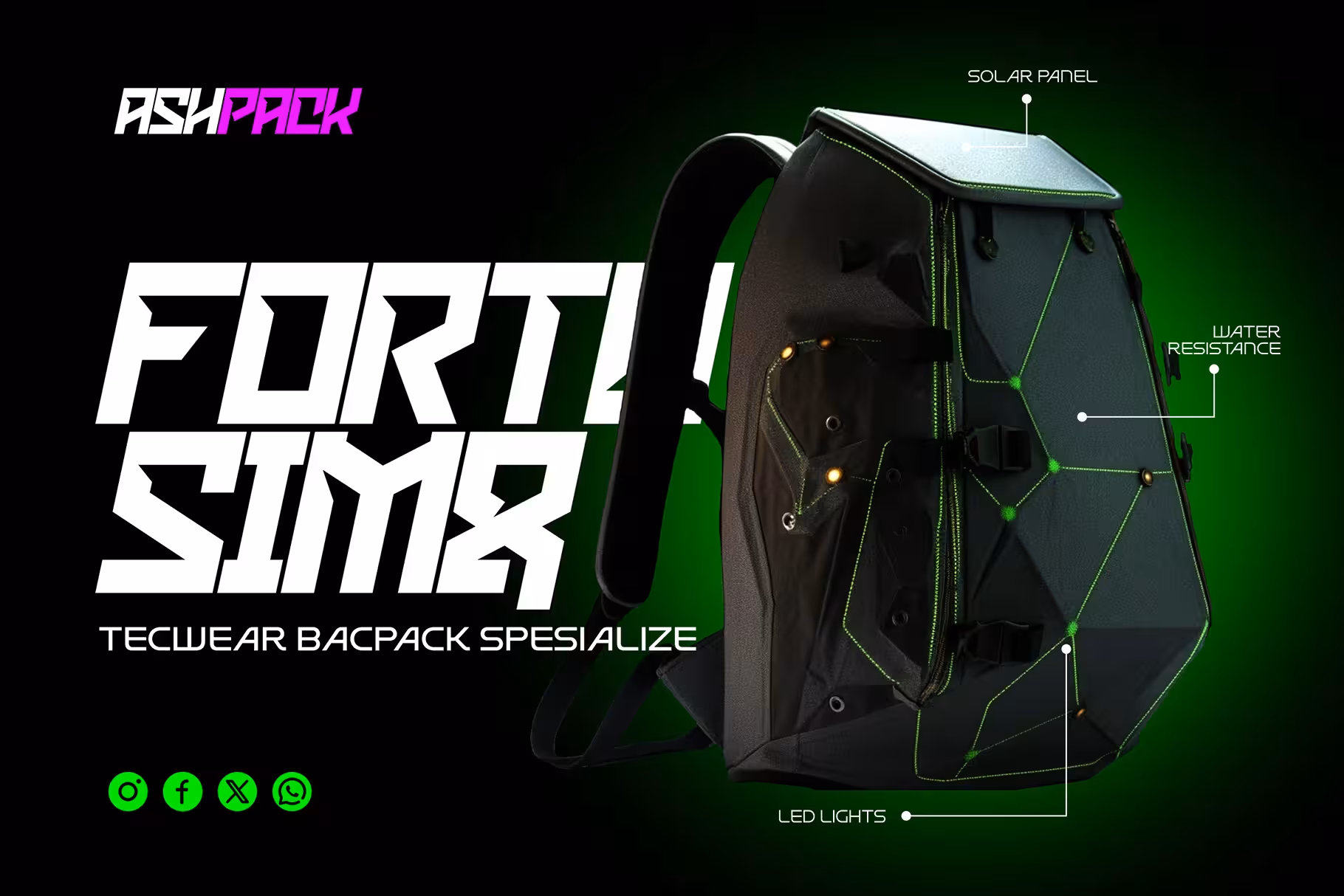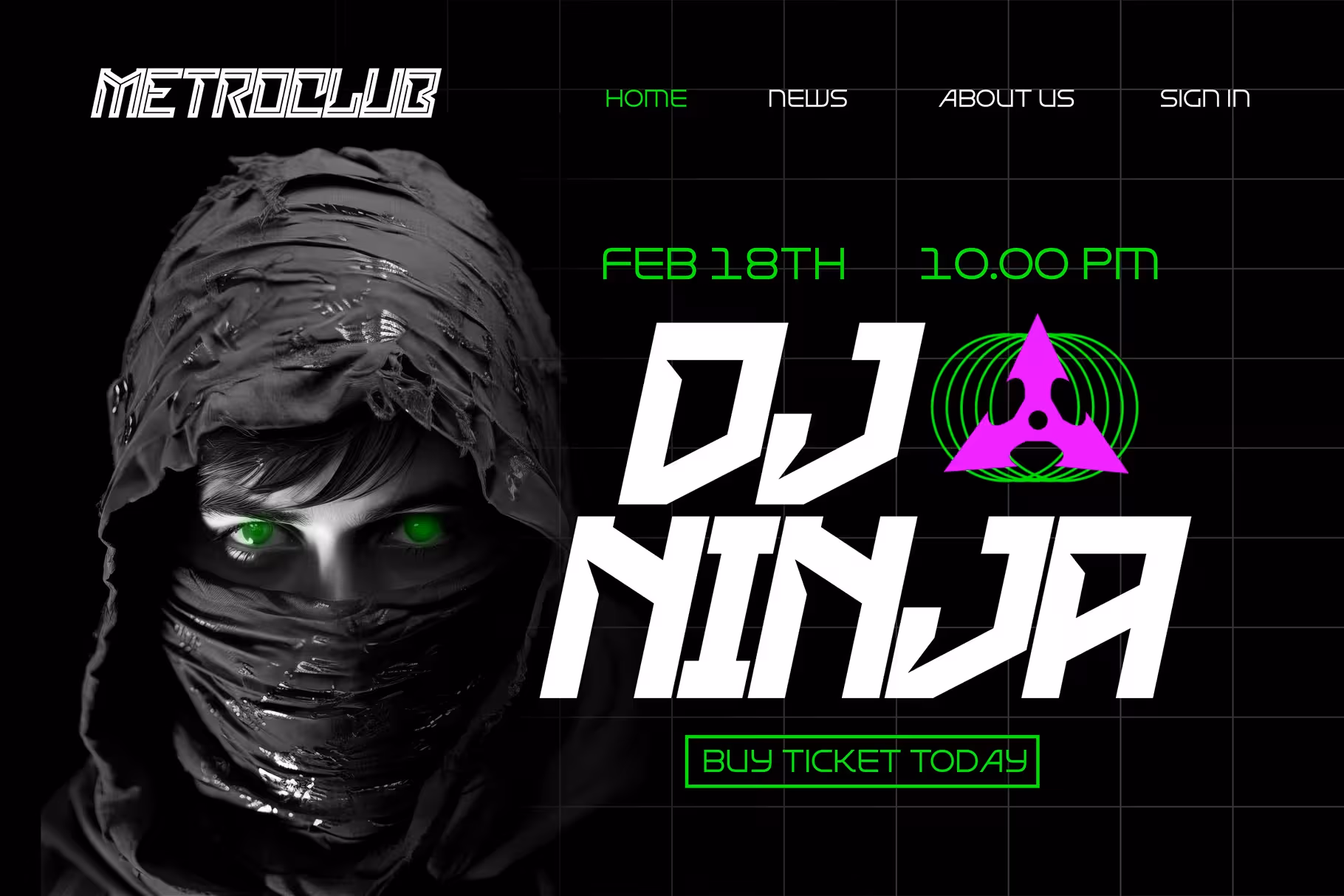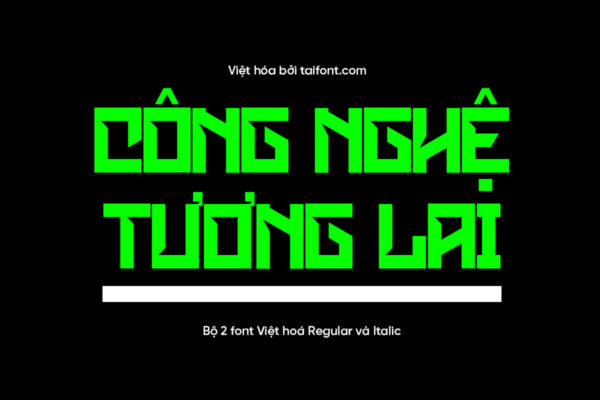
Giới thiệu về Font TF Devolt Strike Regular & Italic Việt hóa
TF Devolt Strike Việt hóa là một bộ font chữ trang trí độc đáo, nổi bật với thiết kế sắc nét, góc cạnh và đầy tính công nghệ, gợi cảm giác về những dòng code, giao diện kỹ thuật số hoặc các yếu tố của thế giới tương lai. Font này toát lên phong thái sáng tạo, mạnh mẽ và đầy ấn tượng, lý tưởng để tạo điểm nhấn độc đáo và thu hút mọi ánh nhìn trong các thiết kế đòi hỏi sự tiên tiến và phong cách khoa học viễn tưởng.
Với đặc điểm thiết kế độc đáo, đường nét dứt khoát và khả năng gợi cảm xúc về công nghệ, Devolt Strike là lựa chọn hoàn hảo cho các ấn phẩm trong lĩnh vực giải trí, công nghệ và tương lai:
- Thiết kế Công nghệ cao và Khoa học viễn tưởng: Hoàn hảo để sử dụng cho logo công ty công nghệ, giao diện ứng dụng, poster phim khoa học viễn tưởng, hoặc các tài liệu quảng bá liên quan đến AI, robot, blockchain. Font này giúp truyền tải sự tiên phong, đổi mới và sự tinh xảo trong từng sản phẩm, dịch vụ.
- Thiết kế Game: Lý tưởng cho logo game, tiêu đề, hoặc các yếu tố giao diện người dùng (UI) trong game có chủ đề cyberpunk, không gian, hoặc các trò chơi tương lai. Nét chữ sắc sảo của font sẽ làm tăng tính chân thực và độ “ngầu” cho trò chơi.
- Poster và Banner: Phù hợp để tạo các tiêu đề chính, slogan, hoặc thông điệp quảng cáo trên poster, banner cho các sự kiện công nghệ, hội thảo, hoặc các sản phẩm muốn gây ấn tượng thị giác mạnh mẽ.
- Thiết kế nhận diện thương hiệu: Có thể dùng cho logo hoặc bộ nhận diện thương hiệu của các công ty, doanh nghiệp trong lĩnh vực công nghệ, gaming, hoặc các sản phẩm mang tính đột phá và hướng tới tương lai.
Với TF Devolt Strike Việt hóa, bạn có thể dễ dàng thổi hồn công nghệ, sự độc đáo và cá tính vào các thiết kế, tạo ra những sản phẩm không chỉ đẹp mắt mà còn cực kỳ ấn tượng và có khả năng thu hút sự chú ý tối đa.